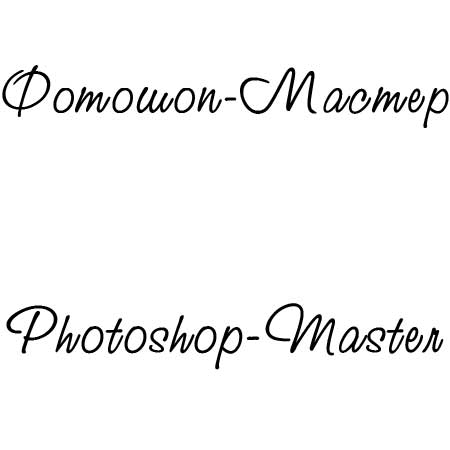
Дополнения Шрифты Татьяна Гапонова 21 февраля 2009 Шрифт - SSR56__C Рукописный шрифт с поддержкой русского языка. Скачать Шрифт - SSR56__C
Мнго раз видела этот шрифт на тетрадях, книгах, учебниках... Теперь знаю его название)